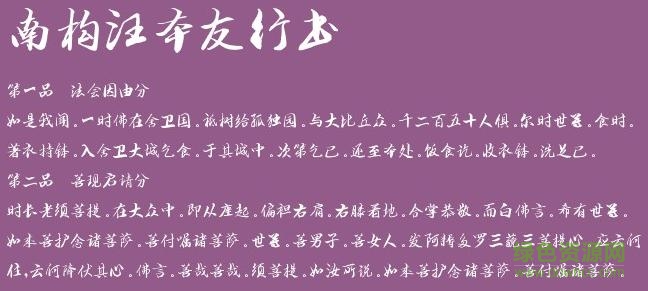
南構(gòu)汪本友行書是一款由汪本友先生創(chuàng)作的行書字體,字形流暢、用毛筆一氣呵成,具有很高的藝術(shù)價值,適合作為字帖練習(xí)行書使用。歡迎大家來綠色資源網(wǎng)下載!
南構(gòu)汪本友行書是一款由書法家汪本友先生書寫創(chuàng)意的毛筆行書字體,字體行云流水,具有很強的視覺沖擊力和實用性,適合用于廣告招牌、海報設(shè)計、標(biāo)題用字等載體。